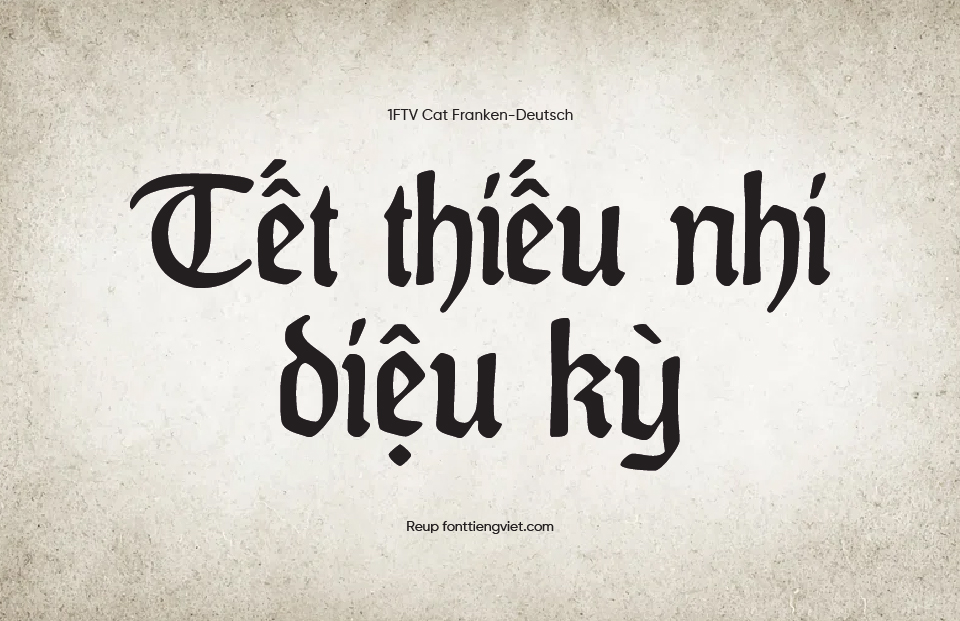
Font Việt hóa 1FTV Cat Franken Deutsch – Font trung thu
Font Việt hóa 1FTV Cat Franken Deutsch – Font trung thu – Lựa chọn hoàn hảo cho thiết kế rằm tháng tám
Giới thiệu về Font Việt hóa 1FTV Cat Franken Deutsch – Font trung thu
Mùa Trung thu đang đến gần mang theo sự náo nức của trẻ thơ và những ánh đèn lồng rực rỡ. Để tạo nên những ấn phẩm truyền thông đậm chất cổ tích, việc chọn một Font Miễn Phí phù hợp là điều cực kỳ quan trọng. Font Việt hóa 1FTV Cat Franken Deutsch – Font trung thu nổi lên như một giải pháp thiết kế độc đáo, kết hợp giữa nét cổ điển Đức và phong cách vui nhộn của những chú mèo, mang lại cảm giác vừa huyền bí vừa ấm áp cho các sản phẩm trang trí lễ hội.
Đặc điểm nổi bật của Font Việt hóa 1FTV Cat Franken Deutsch – Font trung thu
Phong cách thiết kế sáng tạo
Bộ font này được tùy chỉnh để tương thích hoàn toàn với bảng mã tiếng Việt, giúp người dùng không còn lo lắng về lỗi hiển thị dấu câu. Với các đường nét bo tròn mềm mại kết hợp cùng những góc cạnh tinh tế, bộ chữ gợi nhắc đến hình ảnh chiếc bánh nướng, bánh dẻo truyền thống. Đây là lựa chọn lý tưởng cho các bạn học sinh thực hiện báo tường hoặc thầy cô thiết kế phông nền sân khấu phá cỗ tại trường học.
Ứng dụng trong thực tế thiết kế
Không chỉ dùng cho Trung thu, font chữ này còn linh hoạt cho nhiều dự án sáng tạo khác như thiệp mời, bìa sách thiếu nhi hay các banner quảng cáo sự kiện cộng đồng. Sự phá cách trong hình thể chữ giúp thu hút ánh nhìn của trẻ nhỏ, tạo nên không gian lễ hội đầy màu sắc và cảm xúc.